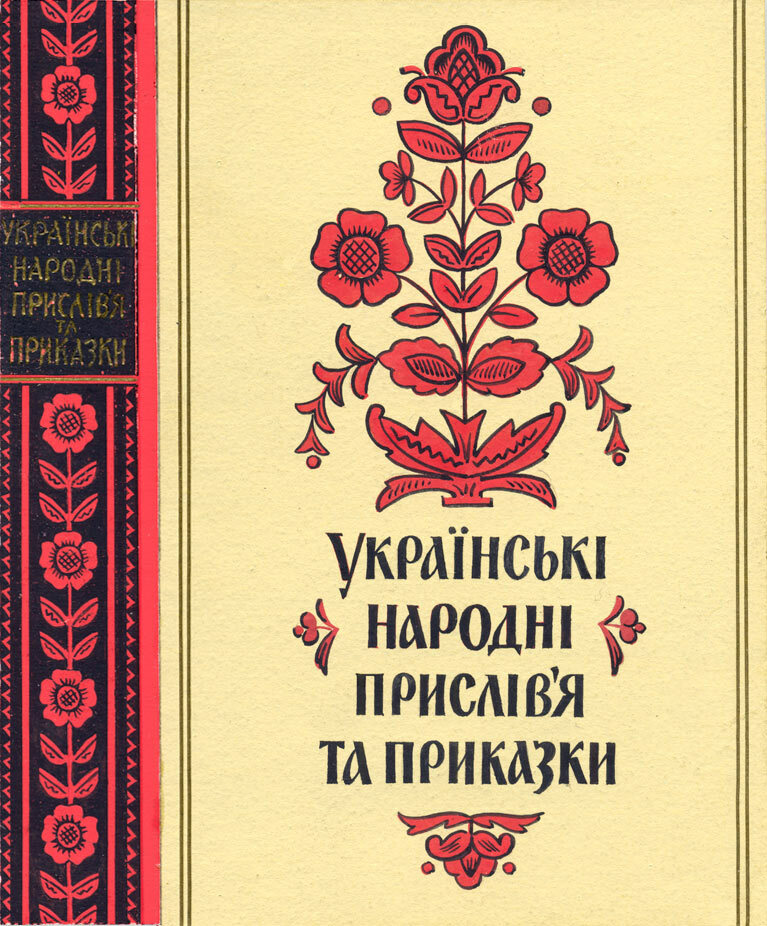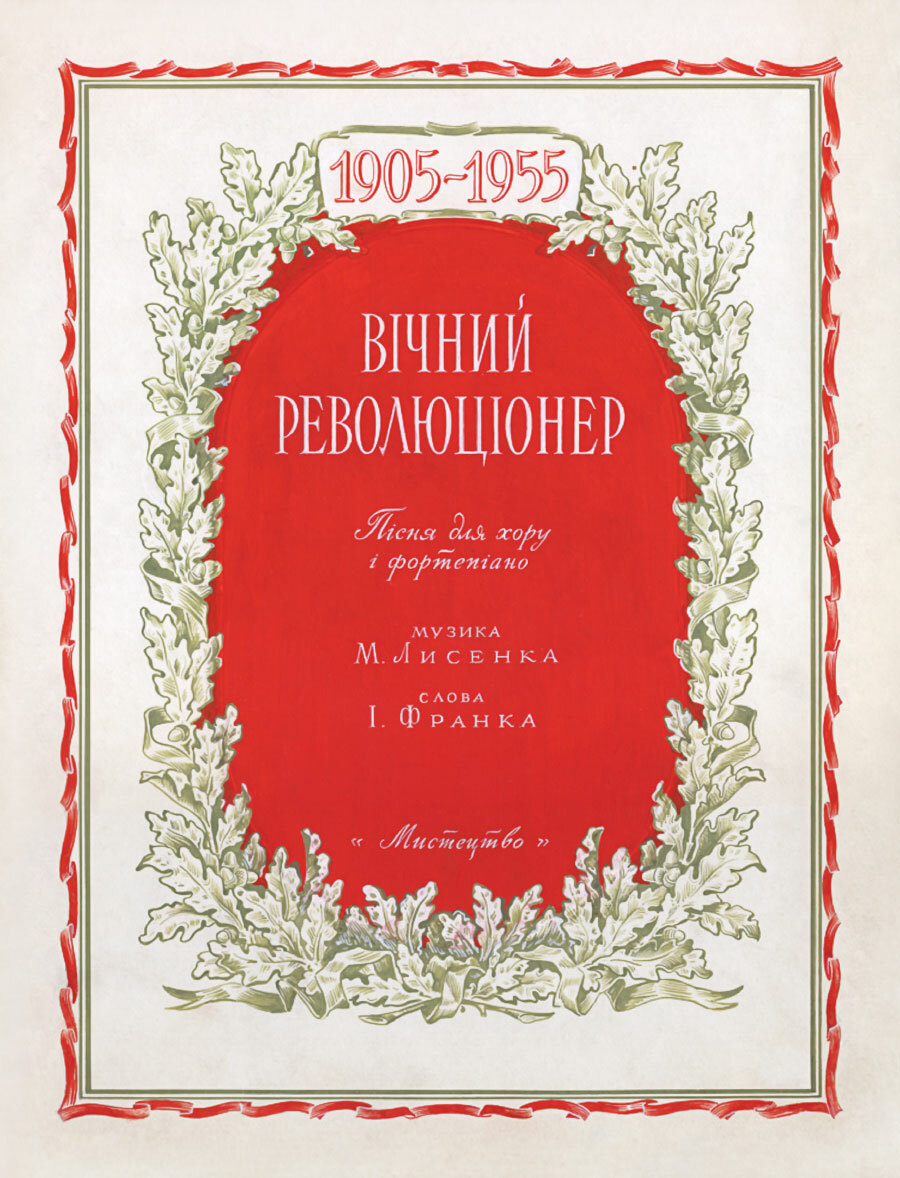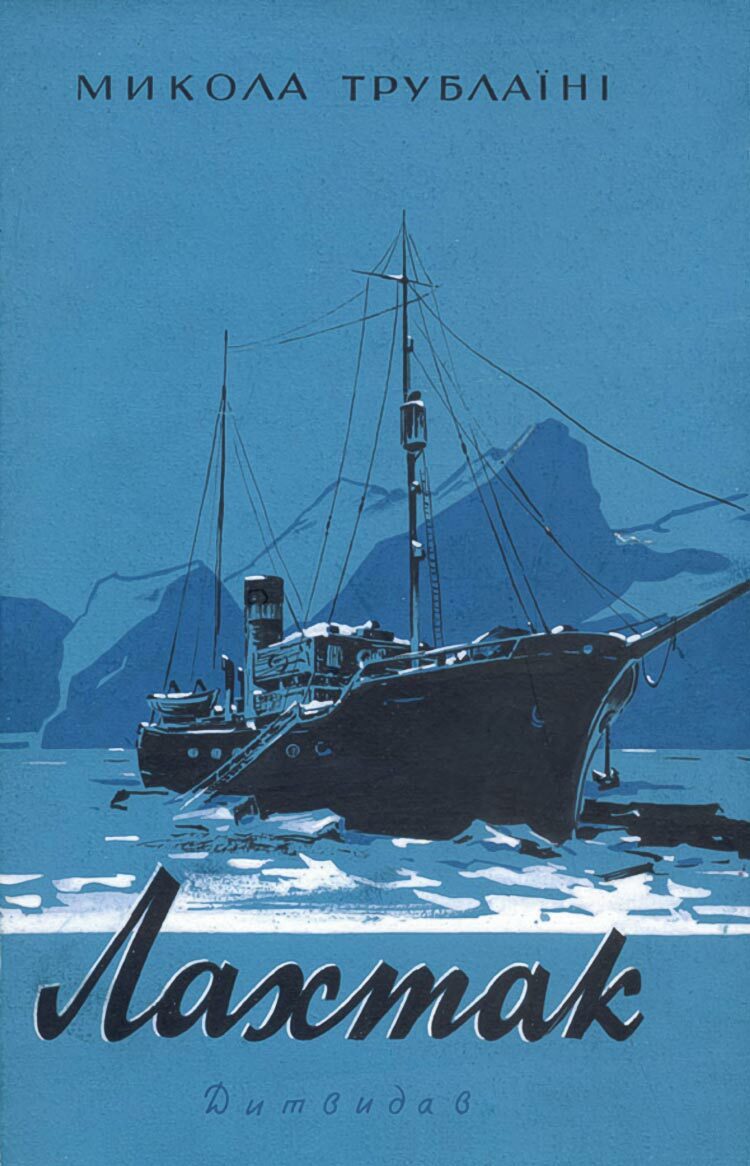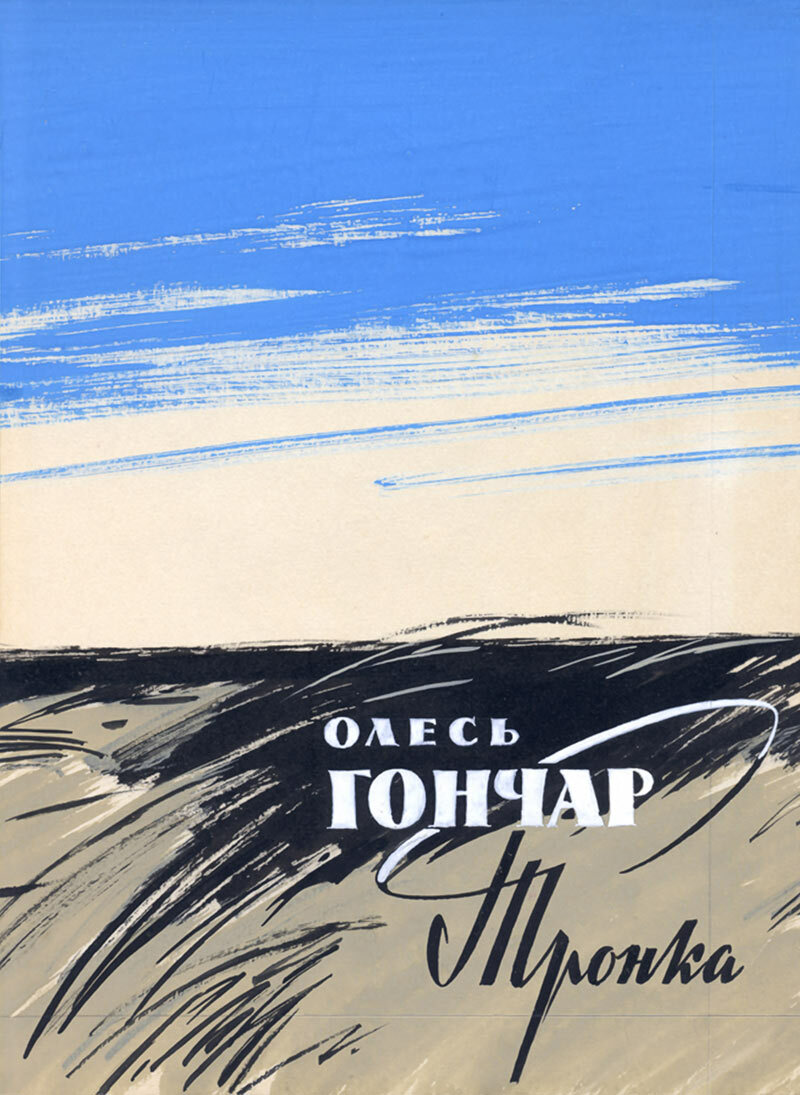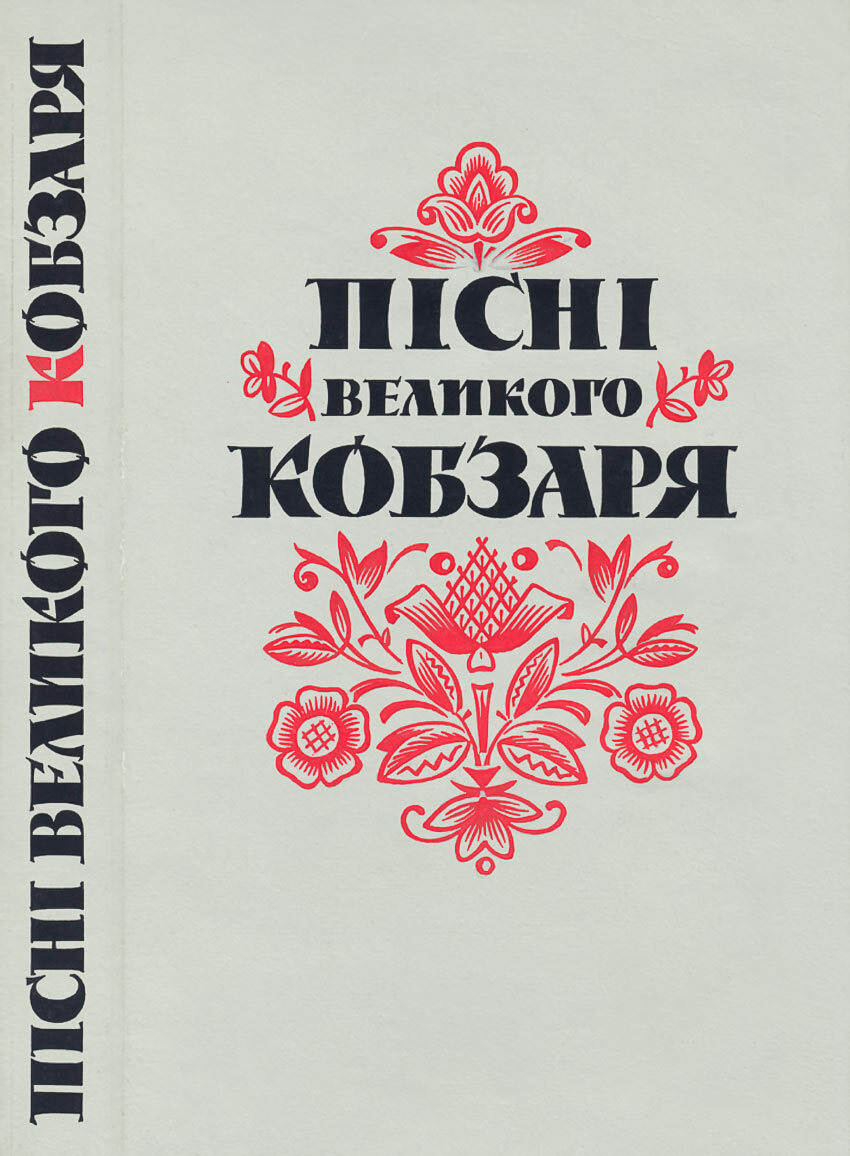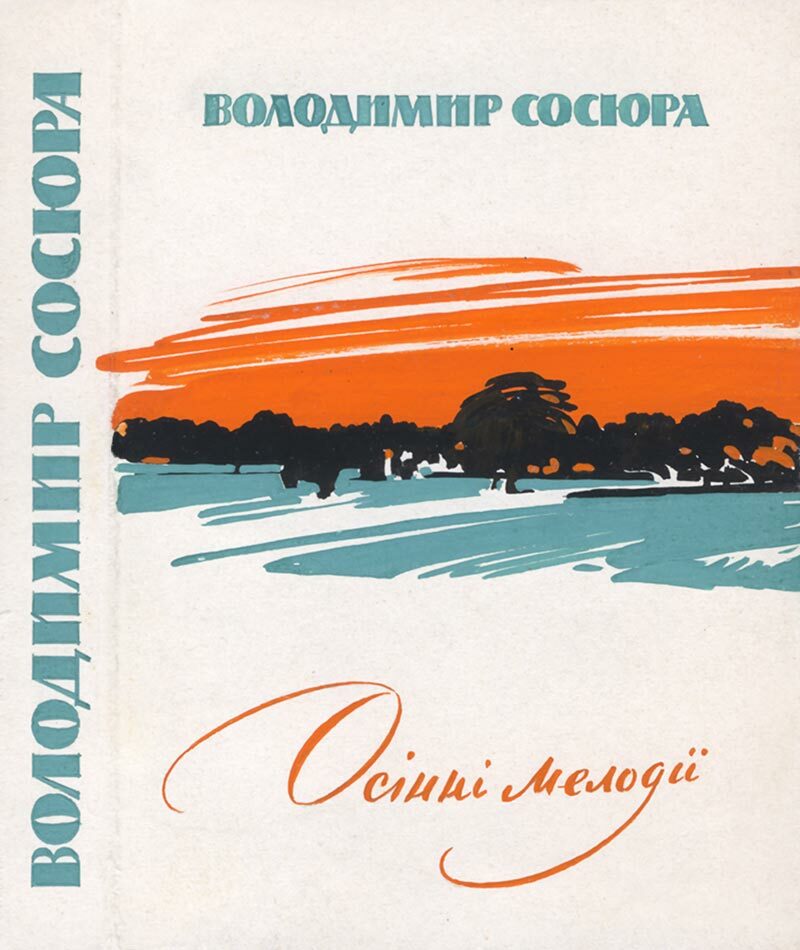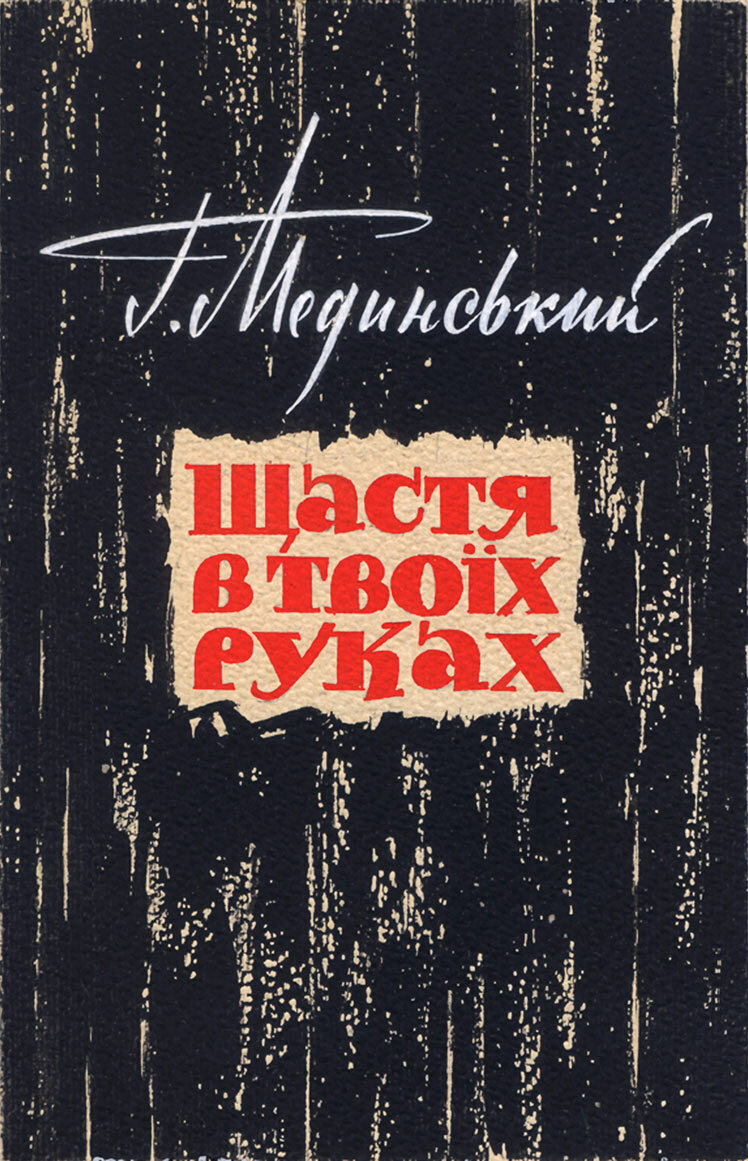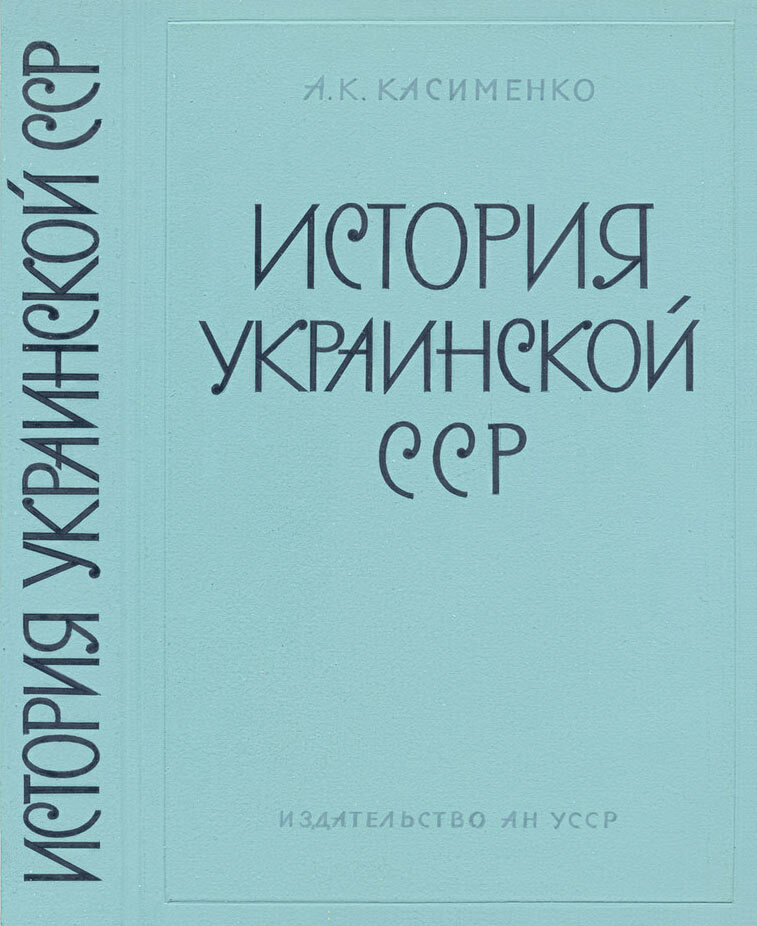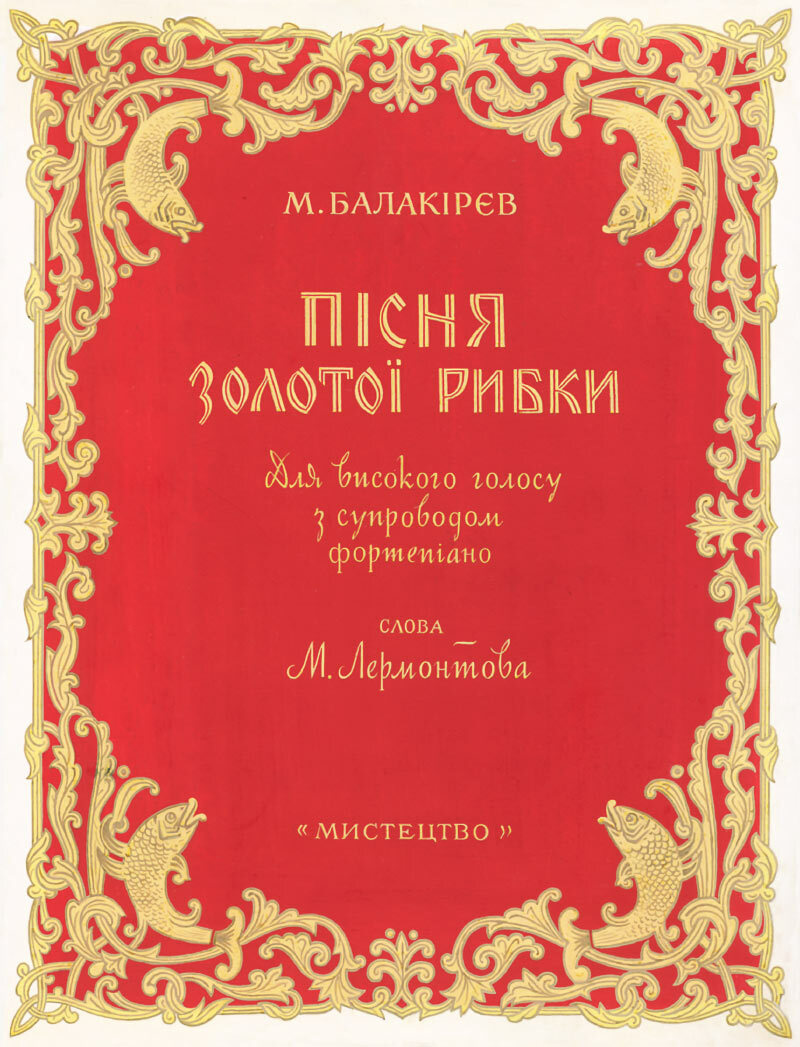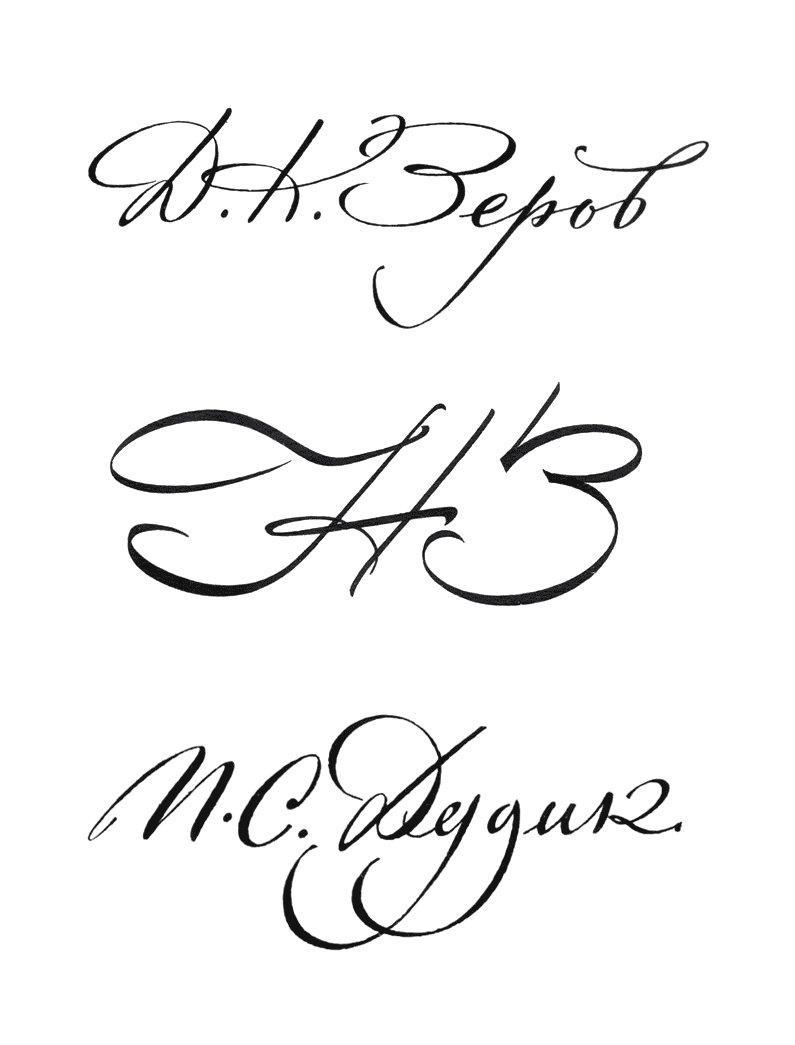
Олександр Ком’яхов (1922–1976)
1965 рік
Книжкова обкладинка. Літерація. Олександр Ком’яхов, 1965, Київ.
1964 рік
Обкладинка книжки «Пісні Великого Кобзаря». Літерація, орнамент. Олександр Ком’яхов, 1964, Київ.
Обкладинка книжки «Осінні мелодії» Володимир Сосюра. Літерація, абстрактна композиція. Олександр Ком’яхов, 1964, Київ.
1963 рік
Обкладинка книжки «Буковинські народні пісні». Літерація, орнамент. Олександр Ком’яхов, 1963, Київ.
Книжкова обкладинка. Літерація, абстрактна композиція. Олександр Ком’яхов, 1963, Київ.
1961 рік
Обкладинка книжки «Український естамп». Літерація, графічний знак. Олександр Ком’яхов, 1961, Київ.
1958 рік
Книжкова обкладинка. Літерація, ілюстрація. Олександр Ком’яхов, 1958, Київ.
1955 рік
Обкладинка. Літерація, орнамент. Олександр Ком’яхов, 1955, Київ.
Обкладинка книжки «Українські народні прислів'я та приказки». Літерація, орнамент. Олександр Ком’яхов, 1955, Київ.
Рік невідомий
Каліграфічний алфавіт. Олександр Ком’яхов, Київ.
Титульний напис. Каліграфія. Олександр Ком’яхов, Київ.
Каліграфічні ініціали. Олександр Ком’яхов, Київ.
Книжкова обкладинка. Літерація, ілюстрація. Олександр Ком’яхов, Київ.
Обкладинка. Літерація, орнамент. Олександр Ком’яхов, Київ.